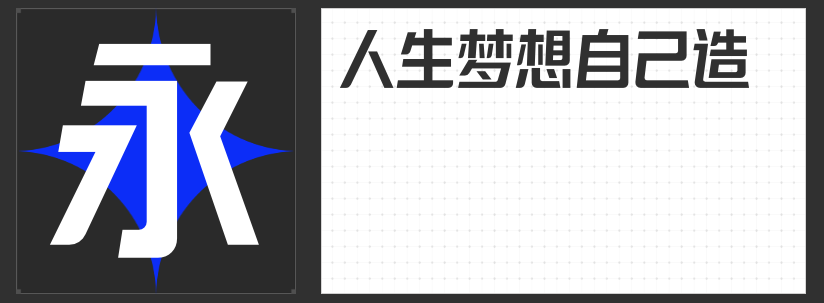
四款风格化字体:解锁海报设计的视觉张力密码
在海报设计的竞技场中,字体不仅是信息载体,更是视觉情绪的催化剂。四款风格迥异的非免费字体,以独特的形态语言打破常规,为海报注入戏剧性张力与情感共鸣。
一、高手字斋哥特体Pro
这款字体以哥特式建筑为灵感基因,通过尖锐的三角衬线与垂直笔画的强化,构建出阴森而庄重的视觉场域。设计师在传统哥特体的基础上融入重金属摇滚的粗粝质感,笔画边缘的微妙锯齿处理,让文字仿佛从锈蚀铁板上生长而出。其核心价值在于瞬间建立压迫性视觉焦点,尤其适合悬疑、奇幻、亚文化主题海报。
二、高手兵克侠客体
横笔画起笔收笔处的飞檐式上扬设计,巧妙复现了中国古建筑的层叠韵律。这款字体通过“横细竖粗”的传统骨架与现代几何化处理的矛盾统一,在复古基调中注入街头潮流的叛逆感。其笔画转折处的圆角处理,既保留了手写温度,又避免过度装饰的甜腻,成为连接传统文化与年轻审美的视觉桥梁,尤其契合新国货品牌与文化展览海报的调性需求。
三、高手庆科帅黑体 大黑
6度倾斜的动态布局打破黑体的静态桎梏,中宫扩张与布白均衡的设计哲学,确保长文本的可读性。设计师通过平切笔画的机械感处理,将传统黑体的庄重转化为未来主义的速度隐喻。西文字符的同步倾斜与直线化改造,构建出跨语言的视觉统一性。这款字体适合科技发布会、运动赛事等需要传递力量与效率的场景,用理性设计语言诠释现代性。
四、励字造梦简 大粗
以摩天大楼的透视结构为灵感,左侧倾斜与右侧垂直的冲突设计制造出强烈的空间纵深感。夸张的笔画粗细对比(横竖比达1:5)强化了视觉冲击力,而棱角分明的切割处理则赋予文字雕塑般的物质感。这款字体通过建筑思维重构汉字形态,适合城市文化、艺术展览等需要表达宏大叙事的海报设计,用字体本身构建视觉奇观。
四款字体均突破传统字形的物理限制,通过形态隐喻传递深层情绪。设计师可根据海报主题选择对应语言体系。